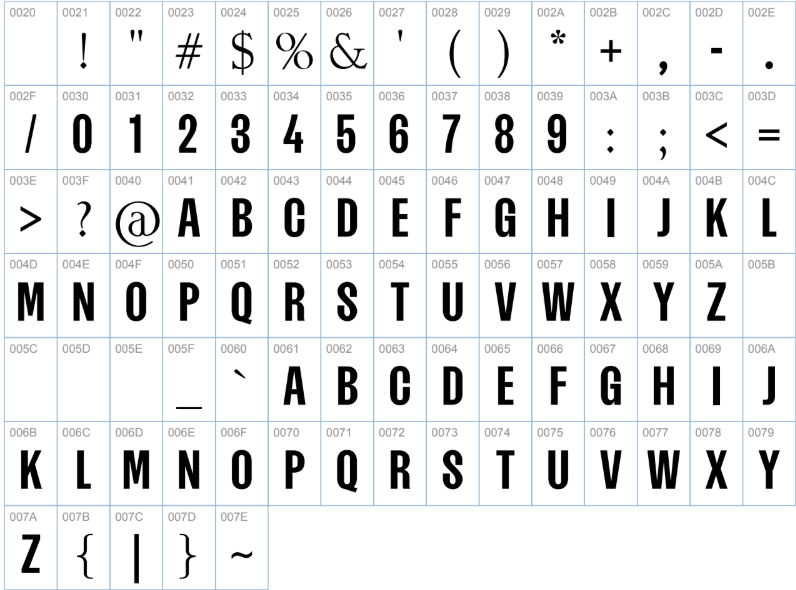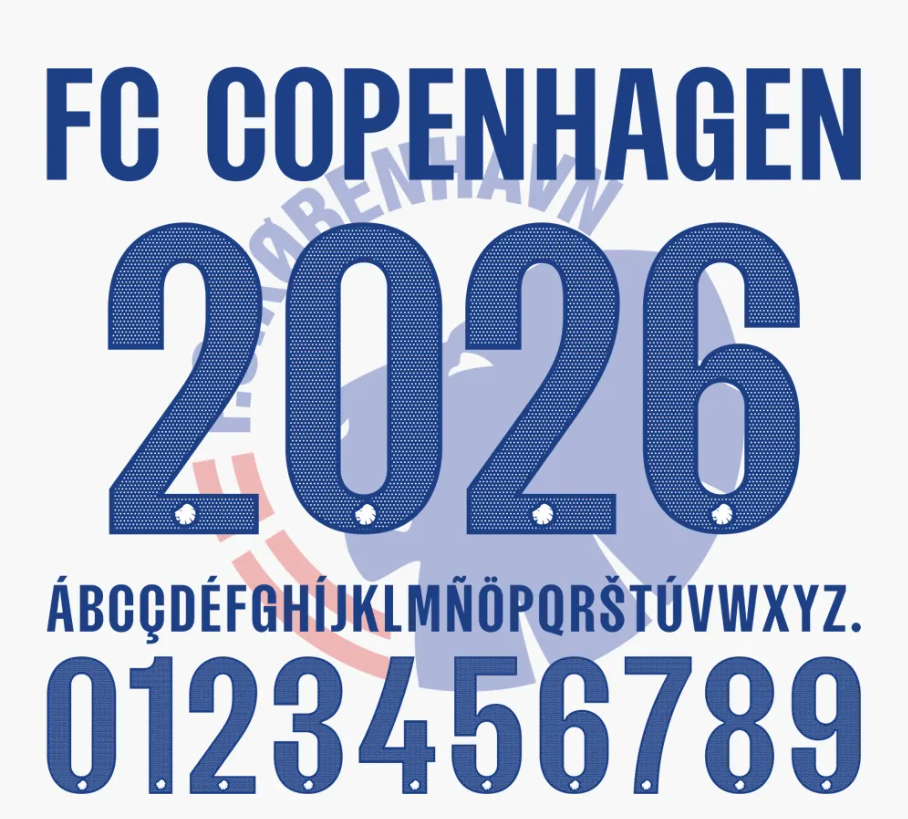
A elegância do futebol escandinavo chega aos seus projetos de design. O FC Copenhagen (F.C. København), maior potência do futebol dinamarquês, mantém sua parceria de sucesso com a Adidas para a temporada 2025/2026, apresentando uma tipografia que reflete a modernidade e o minimalismo típicos da capital da Dinamarca.
- Conteúdo: Alfabeto completo e numeração oficial (incluindo o escudo do clube na base dos números, se aplicável na versão vetorial).
Estilo Visual e Aplicação
A tipografia desenvolvida para o FC Copenhagen segue a nova diretriz global da Adidas para seus principais clubes europeus, mas com toques exclusivos. A fonte apresenta um design “Block” moderno, com cortes angulares que garantem legibilidade a longa distância.
Diferente de fontes genéricas, este estilo visual transmite robustez e limpeza. Ela harmoniza perfeitamente com o branco clássico do uniforme principal e com as cores ousadas dos kits alternativos. É a escolha certa para quem busca um visual “clean”, mas impactante, muito valorizado no design esportivo atual.